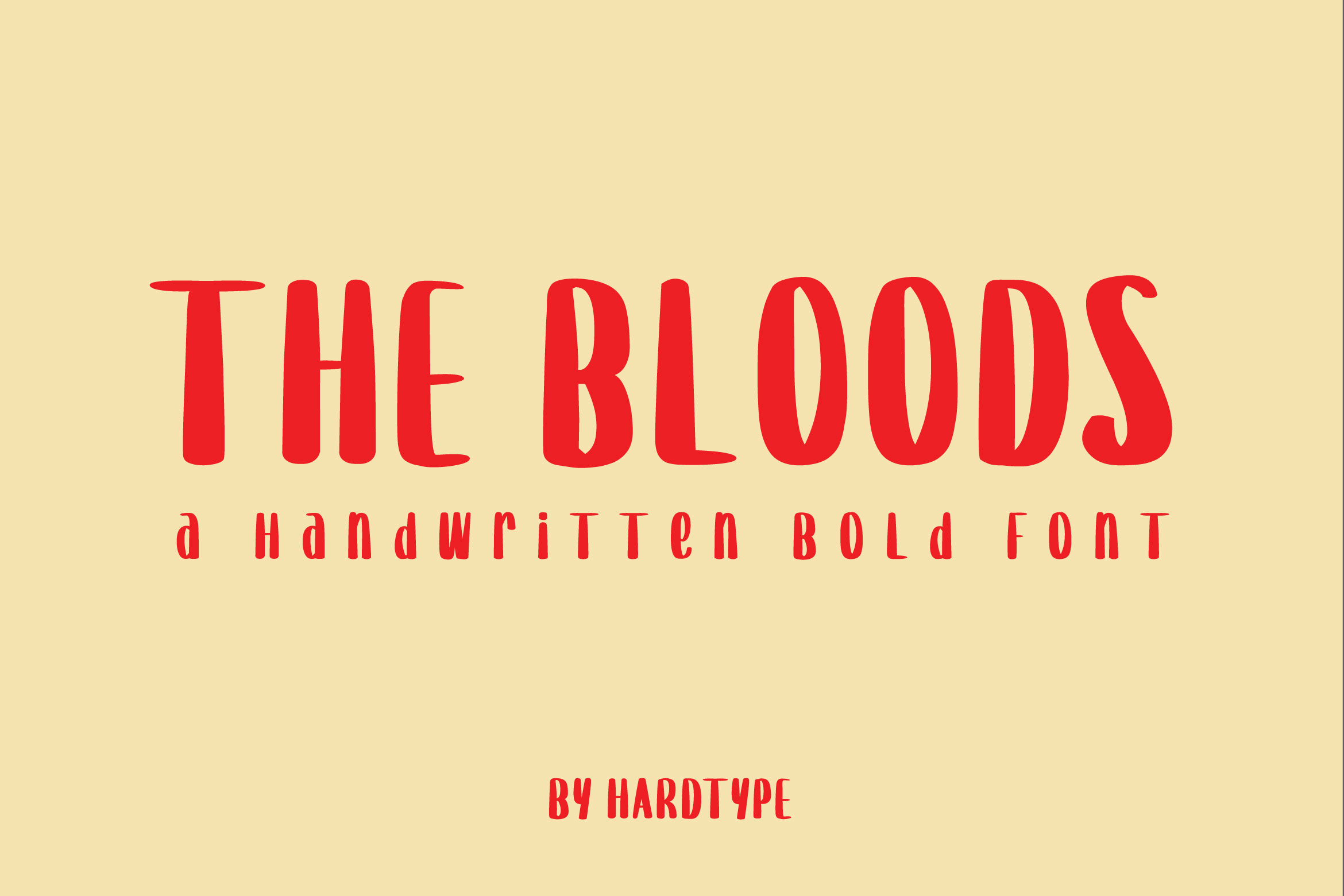
THE BLOODS Font
Designed by Richardwibi
About THE BLOODS
The Bloods adalah font tampilan huruf yang keren, berani, dan tebal. Ini akan meningkatkan berbagai ide kerajinan, dari kartu, hingga branding, label, dan banyak lagi.
Tambahkan dengan percaya diri ke kreasi favorit Anda dan biarkan diri Anda kagum dengan hasil yang dihasilkan.